2025字体设计趋势来了!设计师必看!
“字体设计趋势”正成为 2025 年设计行业关注的核心话题。根据蒙纳最新发布的趋势报告,今年的五大方向分别是:字体设计和多媒体、AI 与字体排印、字体设计与代际延续、字体,冲突与和平、字体设计和环境。这意味着字体不再只是单纯的信息符号,而是进入了更广阔的舞台:它可以与声音、影像结合,展现动态;借助 AI 优化与创作,提升效率;通过代际友好的排版方式,满足不同人群的阅读体验;在社会叙事中承载冲突与和平的对话;在环保议题中发挥推动作用。本文将从这 5 个方向出发,深入解析字体设计趋势,并分享如何通过合适的工具与模板,帮助设计师将趋势落地到实际。
1、字体设计趋势一:字体设计和多媒体
很多设计师在做视频片头、互动广告或展览装置时,常常遇到的问题是:静态字体显得单调,无法承载沉浸感。这时候,“多媒体化的字体”就能派上用场。动态字体可以跟随音乐跳动,在短视频里抓住用户注意力;也可以在 VR/AR 环境中以 3D 的方式悬浮,让观众产生交互感。对于需要做活动宣传视频、互动装置设计、品牌动态视觉的场景,多媒体字体都是不错的解决方案。如果你不知道动态字体设计应该怎么做,不如试试即时设计的字体模板。它的资源社区涵盖了很多免费资源,自然也可以做动效字体设计~
2、字体设计趋势二:AI 与字体排印
如果你曾在排版时因为字距、行距微调耗费大量时间,那么 AI 驱动的字体设计就是解法之一。AI 能自动识别文本结构,帮你生成更合理的排版方案,还能根据不同屏幕与用户习惯进行个性化优化。这类趋势尤其适合做响应式网页设计、移动端阅读体验、需要高效出稿的品牌海报。它不仅帮你节省了机械化的排版时间,还能让设计更贴近不同受众的阅读需求。
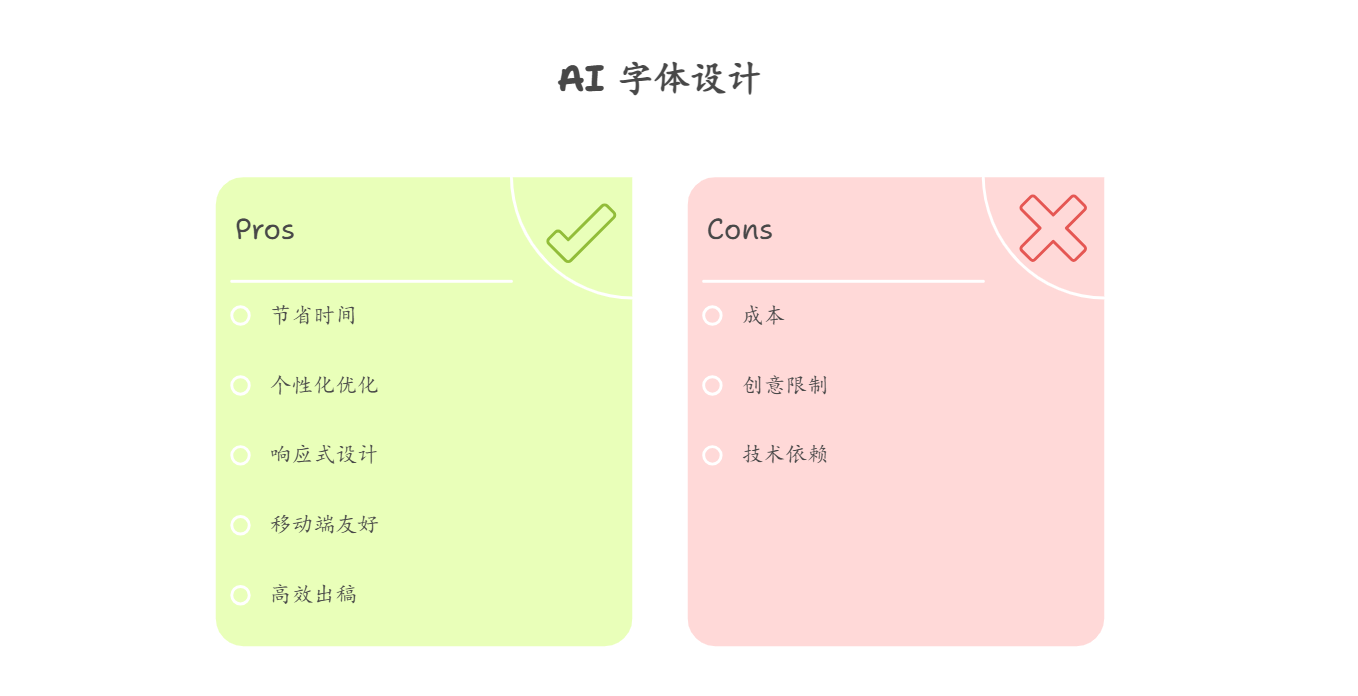
3、字体设计趋势三:字体设计与代际延续
面对不同受众群体时,设计师往往很难做到兼顾:年轻人追求极简和潮流感,中老年群体则希望字体清晰易读。如果不做取舍,排版很容易“失焦”。“代际延续”趋势给出的答案就是可变字体技术——字体可以根据使用场景自动调整,既能在小屏幕上保持可读性,又能在大屏上展现时尚感。它尤其适合教育类读物、跨年龄段用户的品牌设计、公共服务信息化项目,帮助你用同一套字体打通不同群体的体验。
4、字体设计趋势四:字体,冲突与和平
在社会议题或品牌传播中,设计师常常需要用字体来传达立场。比如在公益广告里,想要表达力量与呼吁感,可能会用解构、粗犷的字形;而在节日活动或跨文化交流中,又要用温和、统一的排版来传递包容感。“冲突与和平”的趋势提醒我们:字体不仅是美学符号,更是话语工具。它尤其适合公益宣传、社会议题活动、跨文化交流品牌设计,让字体成为引发共鸣和对话的桥梁。
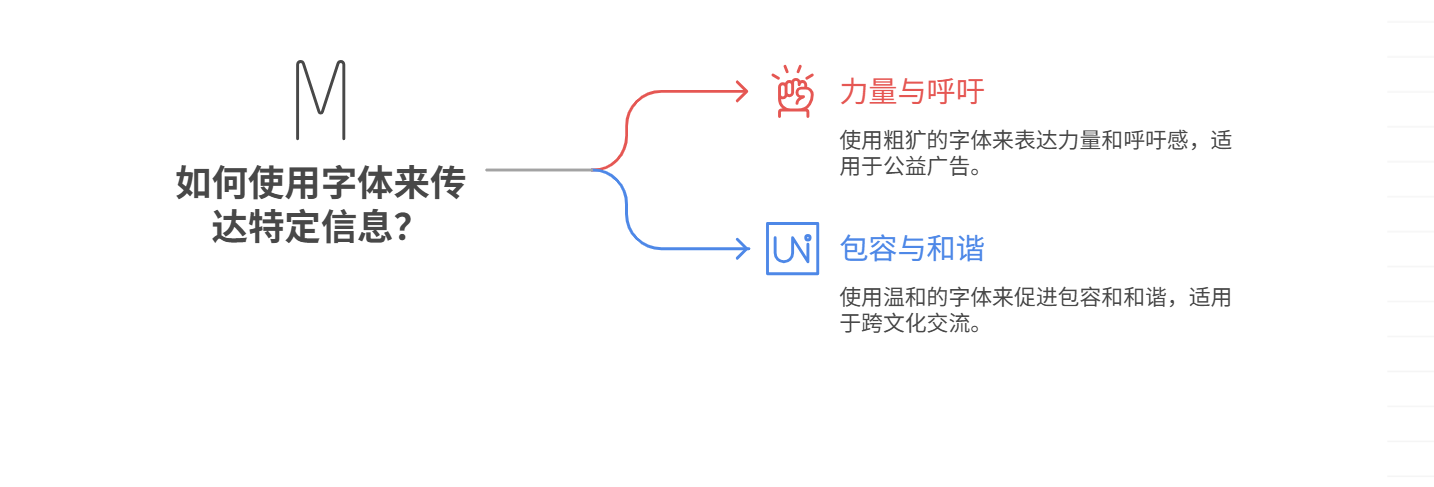
5、字体设计趋势五:字体设计和环境
当下越来越多品牌重视可持续议题,但如何把环保理念视觉化却是难题。“绿色字体设计”提供了新思路:在印刷场景中,简洁的字形可以减少墨水和纸张消耗;在数字场景中,轻量化字体能降低文件加载压力,减少能耗。对于环保主题活动、可持续品牌形象、电商绿色活动宣传,这种趋势都能帮助设计师用字体本身传递责任感和环保价值。
结语
综上所述,2025 年的“字体设计趋势”正朝着多元、智能、共情与责任并行的方向发展。字体已经超越了传统视觉元素,逐渐成为连接人、媒介与社会的桥梁。对于设计师来说,理解趋势只是第一步,更重要的是如何把这些趋势真正落地,转化为实际的作品。通过前文介绍的五个方向,你可以利用相应的模板快速实践。“字体设计趋势”不仅是一份报告中的关键词,它正在变成推动设计行业前进的动力。希望你能借助即时设计的字体设计模板,开启属于自己的创作探索~